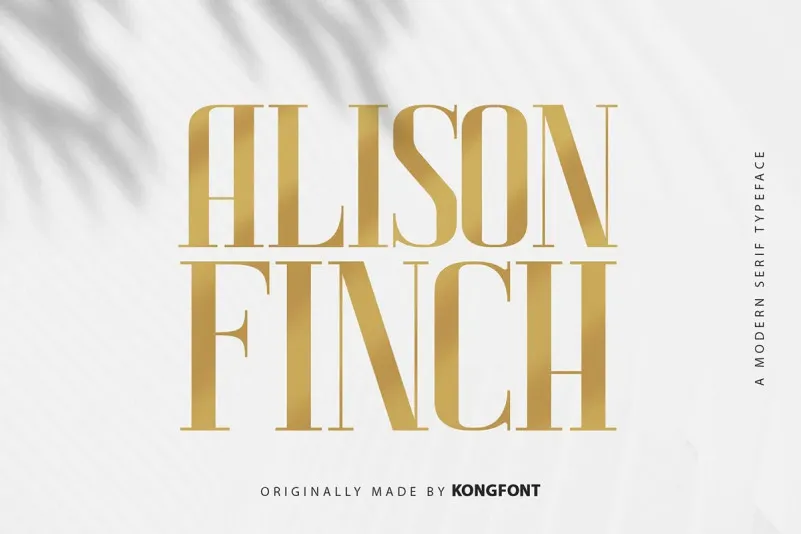
A Alison Finch Font é uma elegante tipografia serif que transmite sofisticação e modernidade ao mesmo tempo. Seu acabamento limpo e refinado revela sua grandeza e grandiosidade imediata, enquanto suas formas expressivas e presença única reforçam seu status. Perfeita para aplicativos que exigem uma escrita sólida e elegante, Alison Finch traz a beleza clássica de uma fonte serif com um toque moderno, tornando-a uma escolha perfeita tanto para projetos profissionais quanto para design editorial. Ideal para editoriais, publicações em jornais ou revistas, e até mesmo para criar marca pessoal, Alison Finch se destaca por sua capacidade de transmitir força e autoridade sem ser pesada. Uma verdadeira fonte elegante que combina a sofisticação clássica com o frescor moderno.